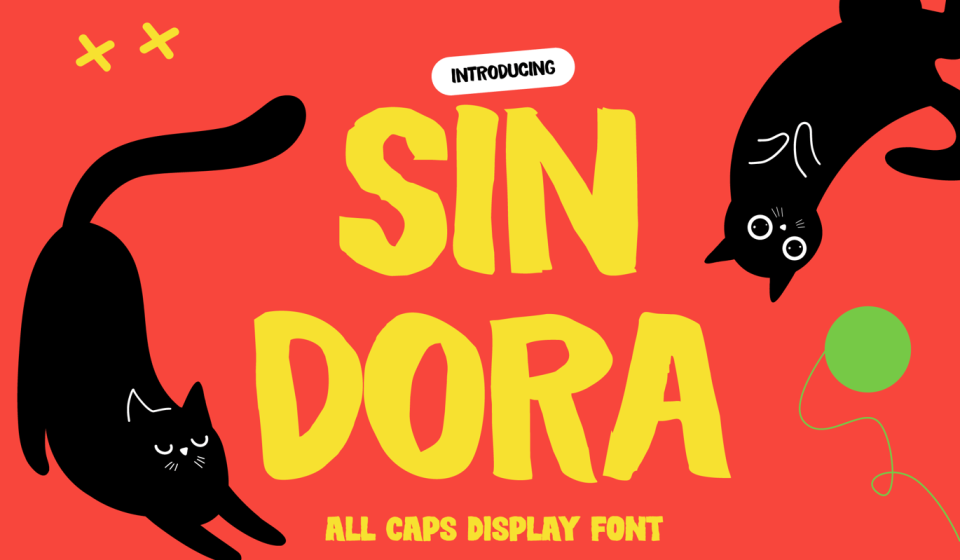
فونت Sindora – تایپفیس جسور، بازیگوش و پرانرژی برای طراحیهای گرافیکی مدرن
در دنیای شلوغ طراحی گرافیک، جلب توجه مخاطب در اولین نگاه هنر اصلی است. فونت نمایشی ضخیم و فانتزی مدل Sindora، یک تایپفیس تمامبزرگ (All-caps) است که با تناسبات ضخیم و منحنیهای نامنظم و عجیب خود، انرژی بازیگوشانهای را به طرحهای شما تزریق میکند. این فونت با ساختار فشرده و کاراکترهای اکسپرسیو (بیانگر)، به طور اختصاصی برای برندینگ مواد غذایی، منوی کافهها و پستهای پرانرژی اینستاگرام طراحی شده است. 🍔🎨
Sindora به هر طرحی شخصیت و شادی فوری میبخشد و باعث میشود عناوین شما با اعتمادبهنفس و لذت در چشم مخاطب جلوه کنند. فونت انگلیسی برای طراحی پوستر و برندینگ غذا Sindora انتخابی بینقص برای طراحانی است که به دنبال انتقال پیامهای مثبت و جسورانه هستند. لبههای دستنویس و فرمهای غیرمتعارف این فونت، حس صمیمیت و دستساز بودن را به بستهبندیها و پوسترهای انگیزشی اضافه میکند تا ارتباطی عاطفی با مخاطبان برقرار کند. ✨📸
ویژگیهای کلیدی و برجسته فونت Sindora
این فونت با تمرکز بر قدرت بصری و جذابیت عناوین، ویژگیهای زیر را ارائه میدهد:
- حروف ضخیم و Chunky: طراحی شده برای جلب توجه حداکثری و خوانایی از فاصله دور. ✅
- اشکال نامنظم و کوئیرکی: اضافه کردن جذابیت بصری و حس بازیگوشی دستساز به طرح. 🎨
- ساختار تمامبزرگ (All-caps): ایدهآل برای تیترهای کوتاه، کوبنده و عناوین اصلی. 🏗️
- جریان انرژی بالا: بخشیدن روح و حرکت به طرحهای ایستا و گرافیکهای تبلیغاتی. 🚀
- پشتیبانی از PUA: دسترسی کامل به تمامی کاراکترها بدون نیاز به نرمافزار طراحی پیشرفته.
کاربردهای اصلی فونت Sindora ⚙️
این تایپفیس برای پروژههایی که نیاز به تمایز و شادی دارند، گزینهای مقتدر است:
- طراحی بنرهای تبلیغاتی و گرافیکهای شبکههای اجتماعی (اینستاگرام و تیکتاک) 📱
- برندینگ تخصصی کافهها، رستورانها و بستهبندی تنقلات 🍕
- خلق پوسترهای انگیزشی و هنری با تیترهای درشت 🖼️
- طراحی تیشرت و محصولات چاپی با شعارهای فانتزی 👕
- عناوین ویدیوها و تامنیلهای یوتیوب برای جلب کلیک بیشتر 🎥
- شامل حروف لاتین A–Z (در دو حالت بصری)، اعداد و علائم نگارشی
نکته مهم: Sindora یک فونت نمایشی (Display Font) است؛ به این معنا که بهترین کاربرد آن در تیترها و متون کوتاه است. استفاده از این فونت برای متون طولانی پیشنهاد نمیشود، چرا که قدرت اصلی آن در بزرگنمایی و ایجاد شوک بصری در عناوین است.